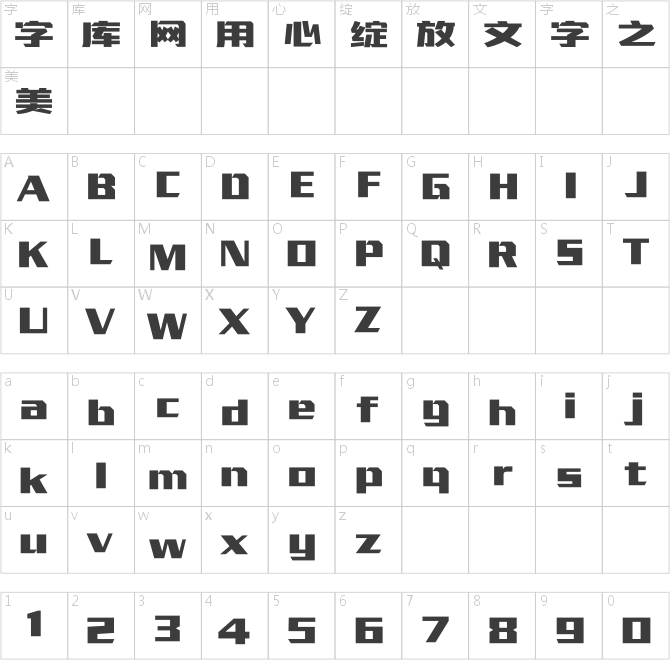
字體名稱: 漢儀曉波鋼古W
漢儀曉波鋼古W
漢儀曉波鋼古W介紹
漢儀曉波鋼古W字體字庫(kù)是一款讓人賞心悅目、百看不厭的中文字體,適合各類廣告和產(chǎn)品包裝設(shè)計(jì)應(yīng)用,字體大小2.13MB,格式為ttf字體,上傳用戶是82年的拉菲,作者/版權(quán)方為漢儀字庫(kù)
漢儀曉波鋼古W效果圖